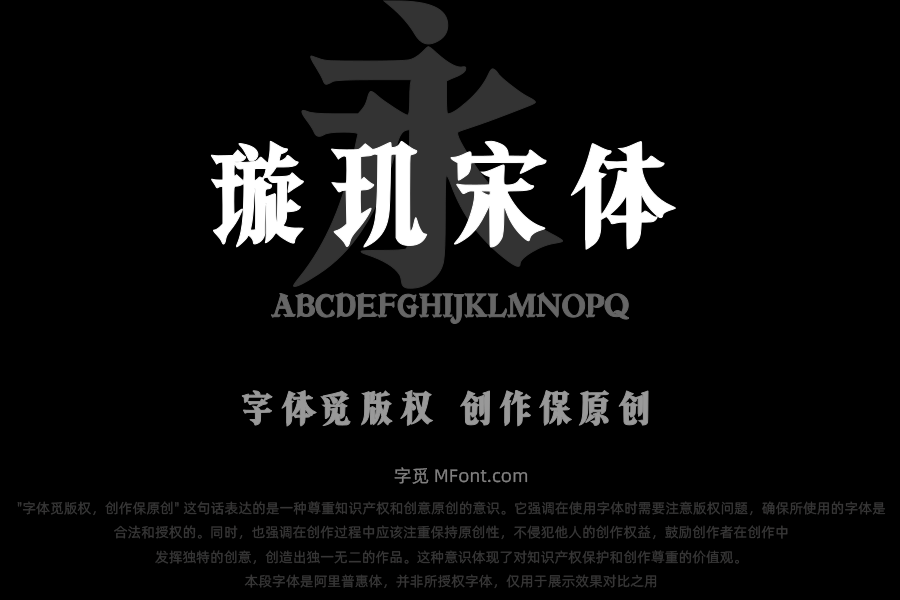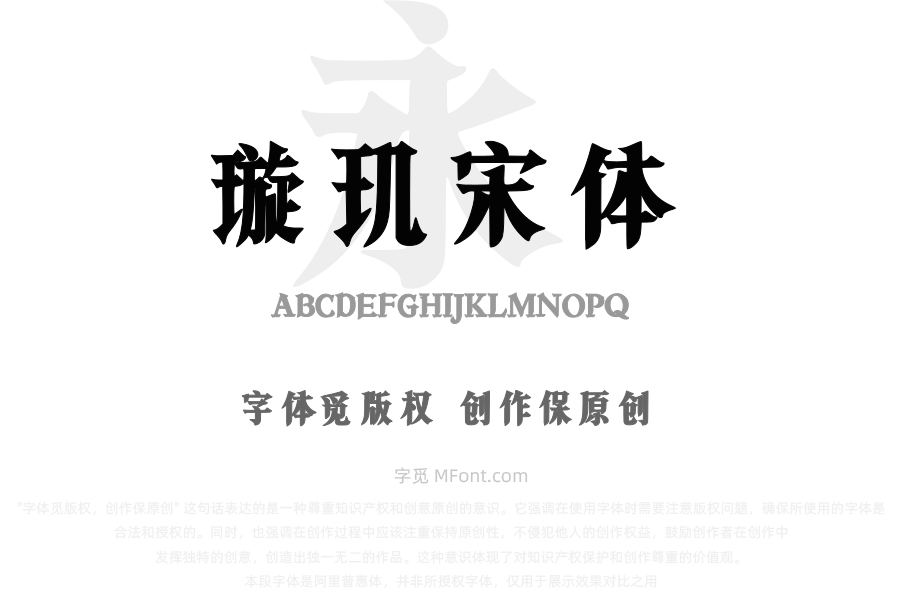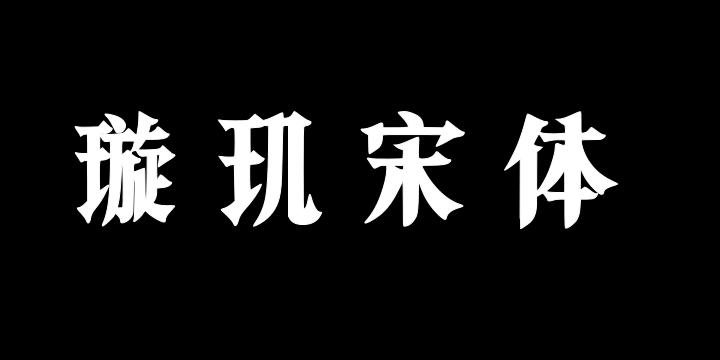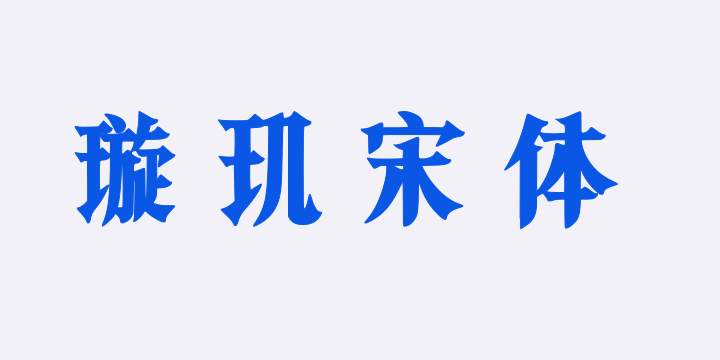
关于东篱璇玑宋体字体字库信息
字体全名: 东篱璇玑宋体
铸字厂: 东篱字库
设计师: 青岛东篱意境设计有限公司
字体简介: 璇玑入字、星汉流墨、宋韵星章、笔尖天象 东篱璇玑宋|让每个字都成为连接古今的星门。紫微垣的帝星坠入宣纸,璇玑玉衡的刻度化作笔锋——我们以《甘石星经》的竹简为骨,敦煌星图的绢帛为肤,在数字深海中打捞起失落的「天文汉字学」。东篱璇玑宋,不仅是字体,更是一场让星宿在指尖流转的文明仪式。